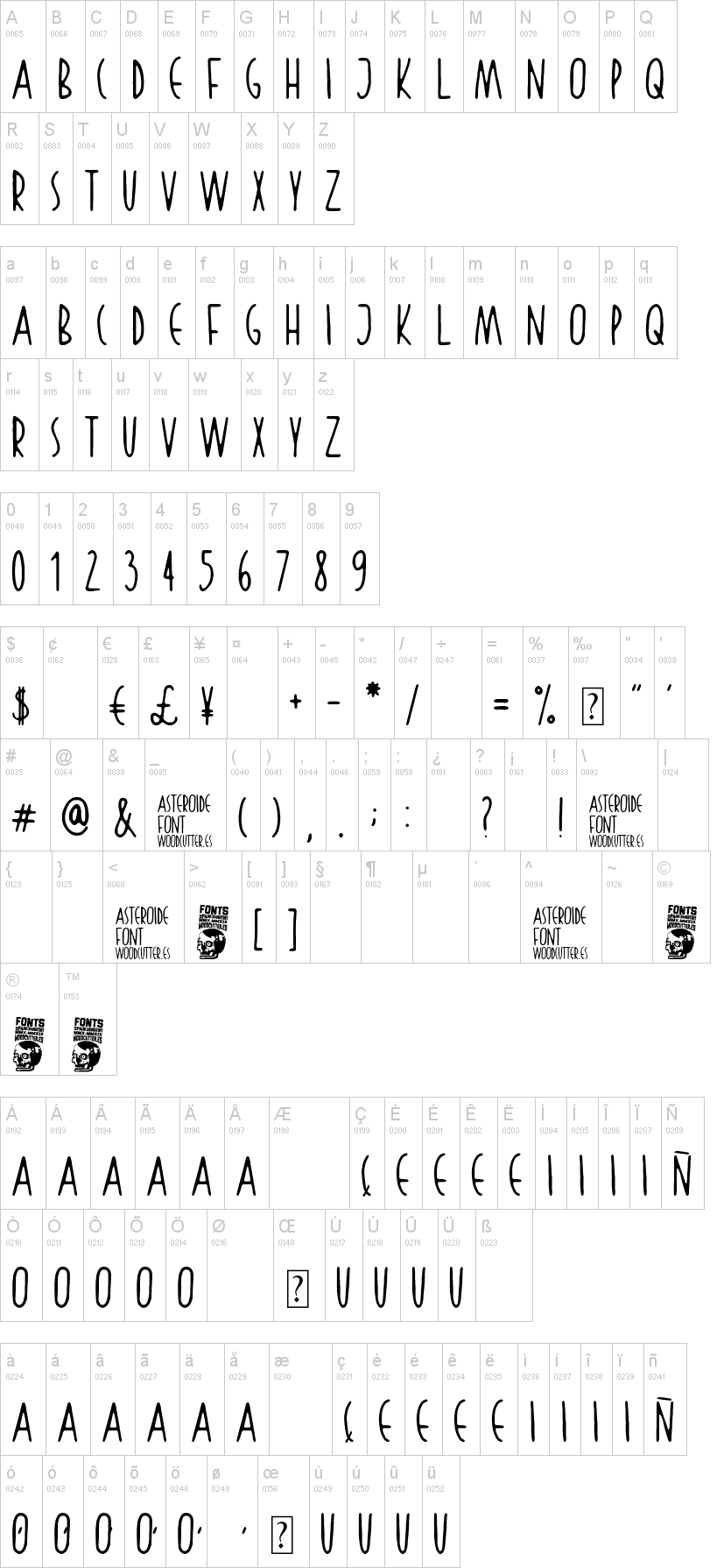
Asteroide 是一种现代风格的无衬线字体,由设计师 Cosimo Lorenzo Pancini 和 Andrea Tartarelli 创作。这种字体的特点是线条简单、直接,形状简洁明了,适合用于各种设计项目,特别是印刷品、品牌标识和数字应用。 Asteroide 字体家族包括四种字重(Regular、Medium、Bold 和 Black),每种字重都有斜体和粗斜体字体样式可供选择。此外,Asteroide 还提供了多种语言支持,包括拉丁字母、西里尔字母和希腊字母,可满足不同语言和地区的需求。 总的来说,Asteroide 字体简洁明了、线条直接,适合用于各种现代设计项目,是一种非常实用的字体。内容介绍
Asteroide是一款非常不错的手写艺术字体,具有很好的视觉感,适合于文化类的宣传设计、商业类品牌的广告和产品包装设计以及个性化文字排版等较多场景。